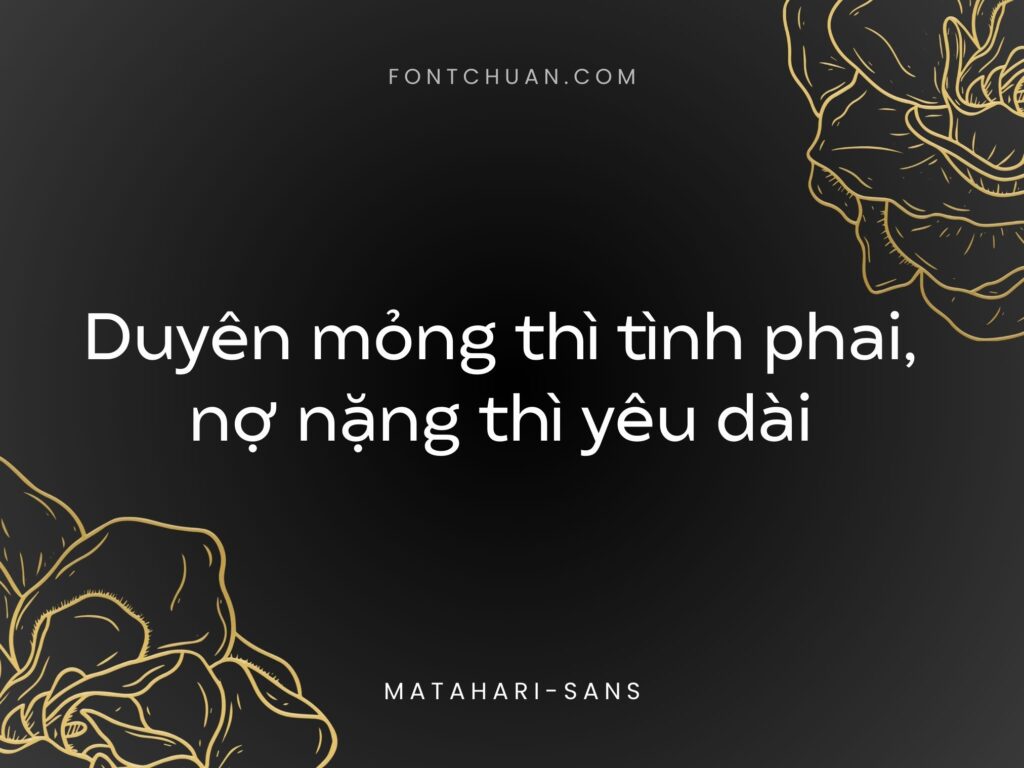
Font Matahari Sans Family Trọn Bộ Font Tiếng Việt
Matahari Sans là một bộ font sans-serif hiện đại, được thiết kế bởi Cahya Sofyan và phát hành bởi Studio Sun vào năm 2019. Lấy cảm hứng từ sự kết hợp giữa các phong cách grotesque và hình học, Matahari Sans mang đến cảm giác thân thiện và dễ tiếp cận. Với 3 độ rộng và 7 trọng lượng, cùng phiên bản nghiêng cho mỗi font, bộ font này cung cấp sự linh hoạt cho nhiều mục đích thiết kế. Matahari Sans hỗ trợ tiếng Việt và nhiều ngôn ngữ khác, được sưu tầm và đăng bởi thành viên của Font Chuẩn.
Với cấu trúc chữ rõ ràng, độ dày nét đồng nhất và các đường nét mềm mại, Matahari Sans tạo nên sự cân bằng giữa tính thẩm mỹ và khả năng đọc, lý tưởng cho các thiết kế thương hiệu, truyền thông xã hội, tiêu đề và nội dung số. Bên cạnh đó, Matahari Sans còn là một Font chữ bất động sản phù hợp cho các dự án như thiết kế hồ sơ dự án, biển hiệu, bảng quảng cáo và các ấn phẩm truyền thông cho các dự án nhà ở hoặc khu đô thị, giúp mang lại cảm giác chuyên nghiệp và hiện đại. Ngoài ra, font này cũng thích hợp cho các sự kiện như lễ hội, sinh nhật, ngày Nhà giáo và Valentine.